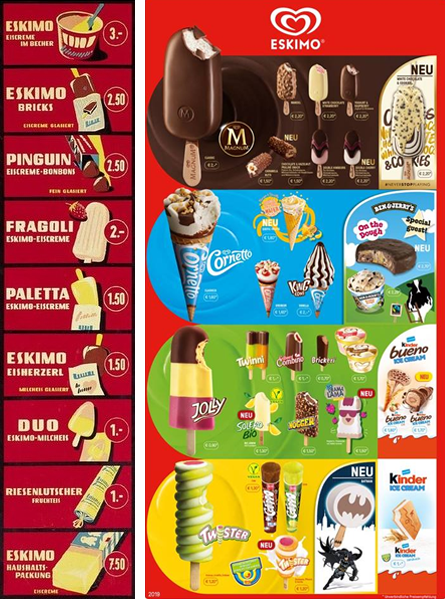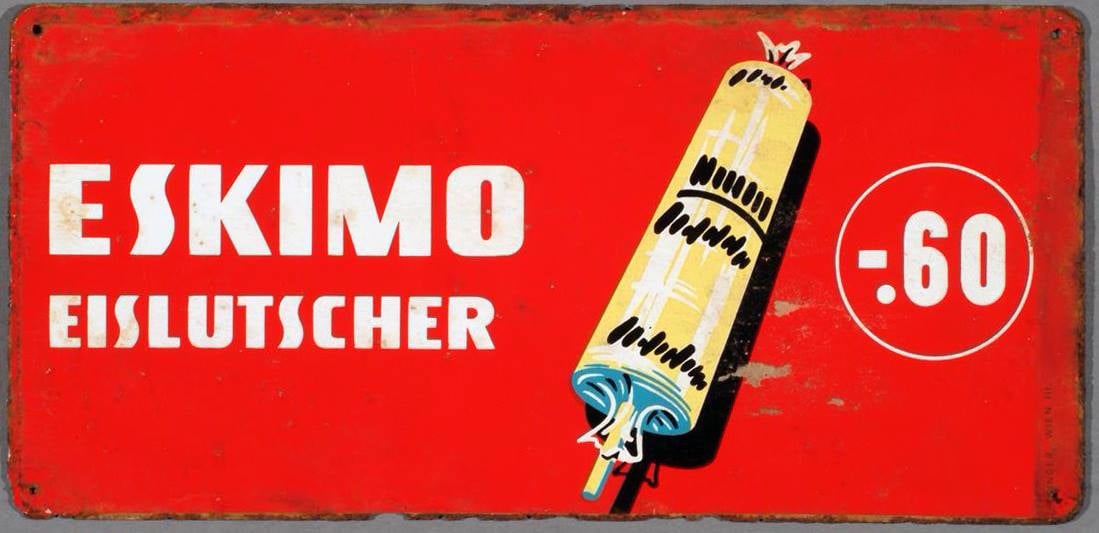
Liebe Schriftwissende, ein Bekannter behauptet, beiliegendes Eskimo-Schild wäre aus den 1960ern. Mir kommt das nicht recht glaubhaft vor, die Schrift paßt mir so gar nicht dazu. Ich habe in unserer alten Bleisatz-Druckerei Plakatschriften aus den 30er-Jahren, die diese S-Form schon zeigen. Auch gestalterisch...nein, ich glaub´s nicht recht. Kennt irgendwer das Schild? Könnt Ihr es einordnen anhand von Schrift, Form, Bild? Es wäre ganz toll, wenn hier jemand mir weiterhelfen könnte - lieben, lieben Dank!
Als ich in den 60ern Kind war, kostete ein Eis ähnlicher Art tatsächlich um die 60 Pfennig … in den 30ern dürfte das zu viel Geld gewesen sein. Wenn man anderen, ähnlichen Tafeln im Netz vertrauen darf, zu denen die 50er- und 60er-Jahre als Veröffentlichungszeitraum genannt werden, dürfte dein Bekannter Recht haben. Für die 30er wäre die flächige Gestaltung auch wohl zu avantgarditisch; gerade die Farb- und Formgebung (in der grafischen Gestaltung) am unteren Ende des Eislollis spricht auch eher für die 60er-Jahre.
Die Schrift an sich (vgl. z. B. die ähnl. Koloss aus den 1920ern) ist sicher »älter«, aber auch für die Werbung im »Mid-Century« nicht unüblich.
Ich habe nach Eskimo-Eis eine Google-Bildersuche gemacht, und dieses gefunden: Die linke Spalte mit der Schrift aus dem Schild ist von 1960
Das wienmuseum.at hat genau dieses Eislutscher-Schild und datiert es in die 60er Jahre: